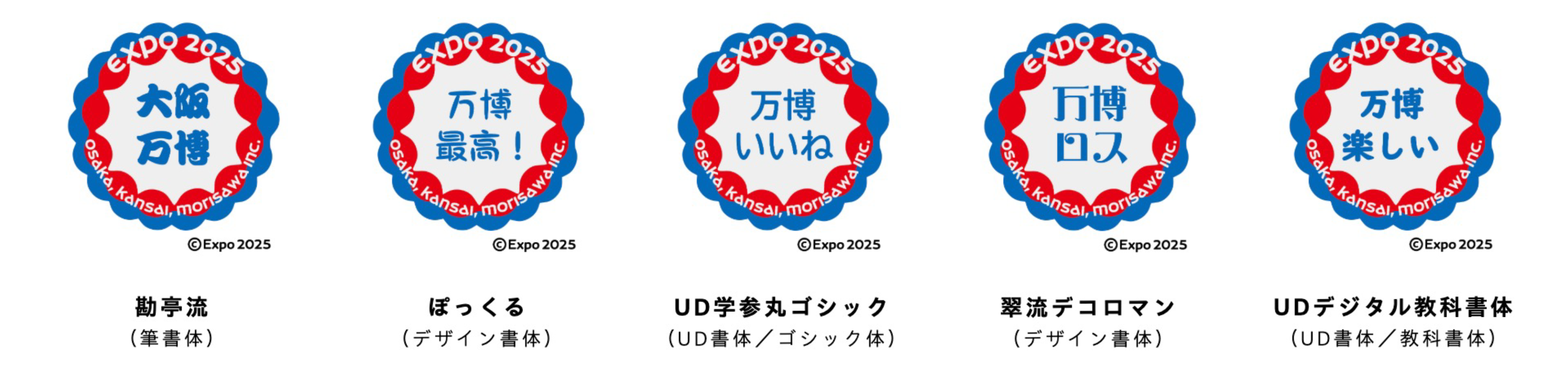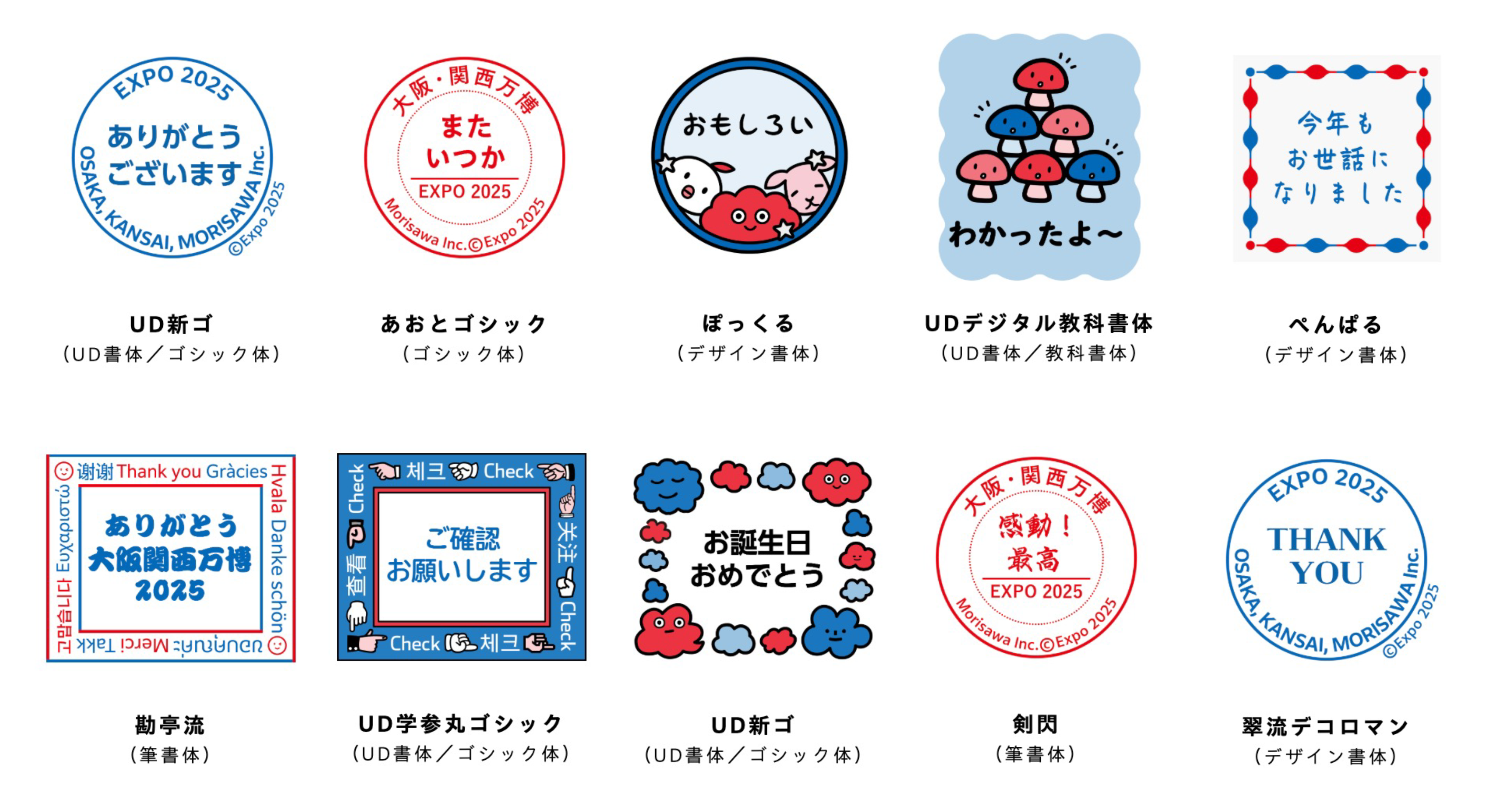
モリサワ フォント選びの楽しさ伝える「大阪・関西万博特設サイト」で作成されたデジタルスタンプは2万個以上〜人気はUD新ゴや翠流デコロマン〜
「フォント de スタンプ」サイトは、大阪・関西万博モチーフのデザインを含む9種類のフレーム(台紙)とモリサワのフォントを使って、好きな言葉やお名前を入力してオリジナルのデジタルスタンプを作成、ダウンロードすることができました。2025年8月6日の公開から87日間で、のべ24,511個のデジタルスタンプを作成いただき、SNSなどでもご活用いただきました。
最も多くの方に選ばれたフレームは、EXPO 2025を「Gasket Uncial」という個性的な欧文フォントで表現し、フォントに含まれている記号(「瓦明朝」を使用)を万博カラーの赤と青で組み合わせてデザインしています。万博を応援するたくさんのメッセージをはじめ、さまざまなスタンプを作成いただき、「みんなのスタンプギャラリー」を飾っていただきました。
また、「フォント de スタンプ」でデジタルスタンプを作成いただく際に、年代やフォントへの関心の有無、文書などを作成する際にフォントを選ぶかどうかなどの簡単な質問に回答していただきました。年代別の傾向では、筆書系デザイン書体「剣閃」は年代が低くなるにつれ人気でした。また、「フォントを頻繁に選ぶ」と回答した方は「翠流デコロマン」や「ぽっくる」などデザインフォントを選ばれる方が比較的多く見られました。一方、「フォントを選ばない」または、フォントを使った文書や写真加工などを「作らない」と回答した方は「UD新ゴ」や「リュウミン」などゴシック体や明朝体など、案内サインや書籍など身近な場面で使用されることの多いベーシックなフォントを選ぶ傾向が表れました。